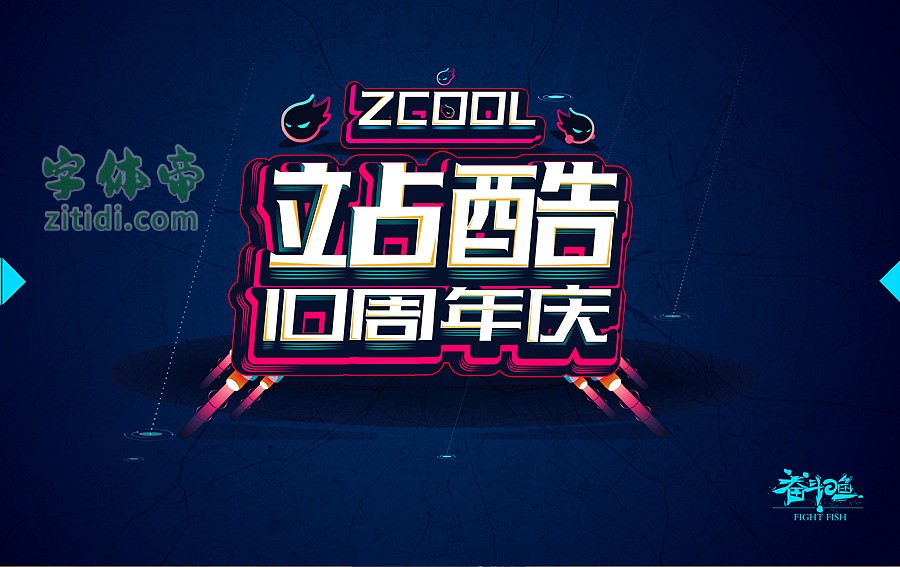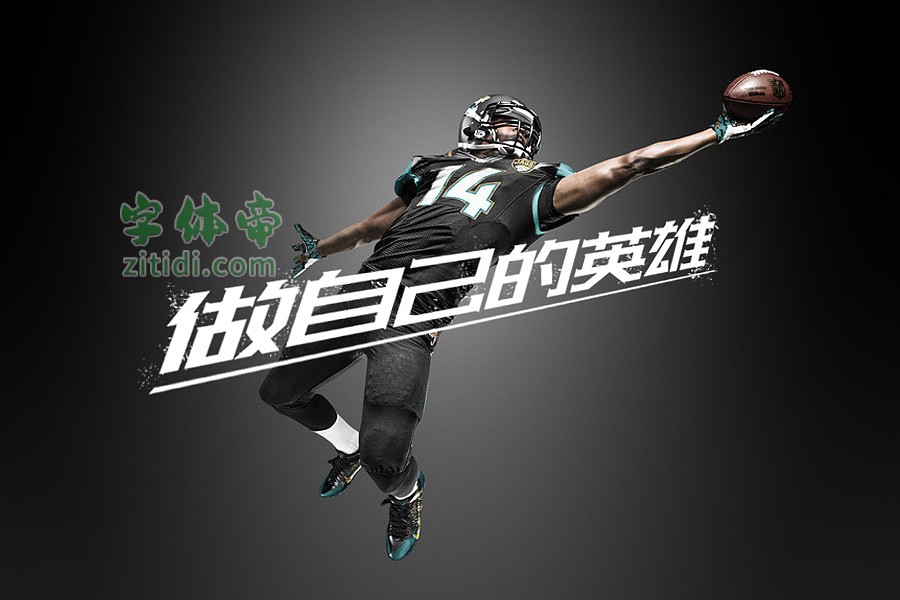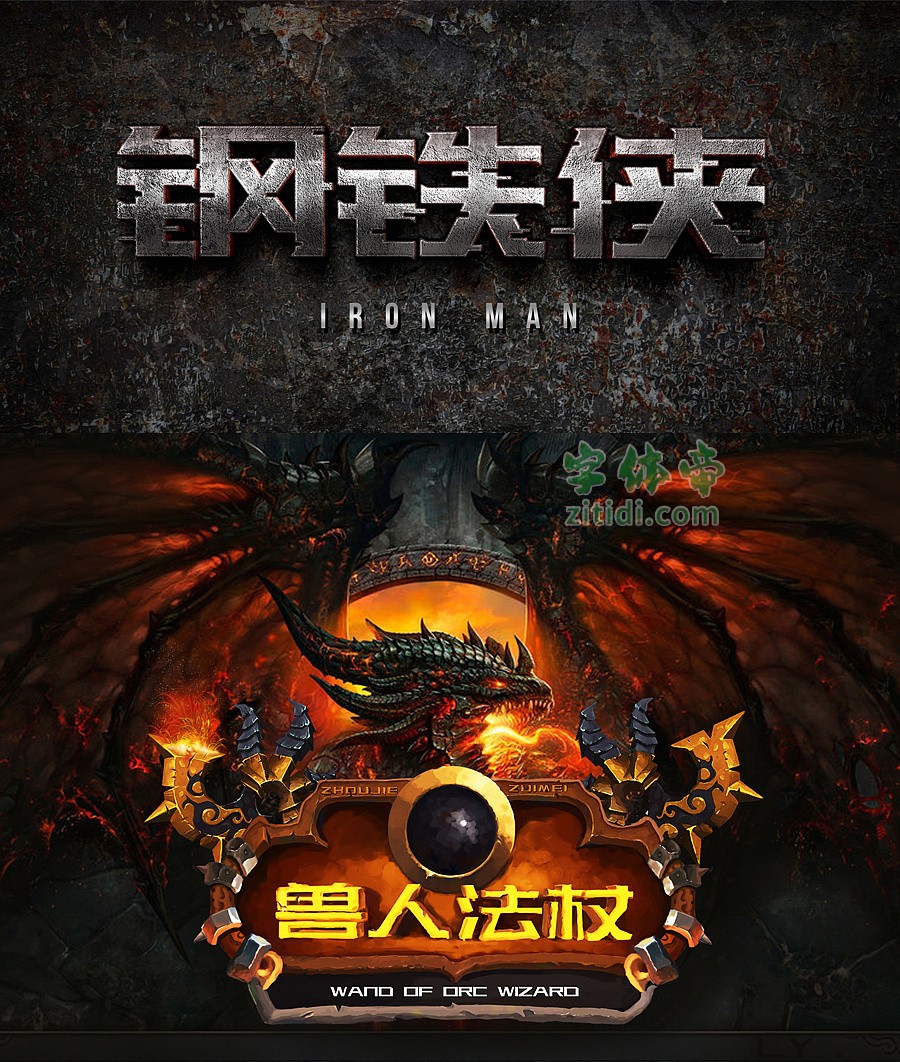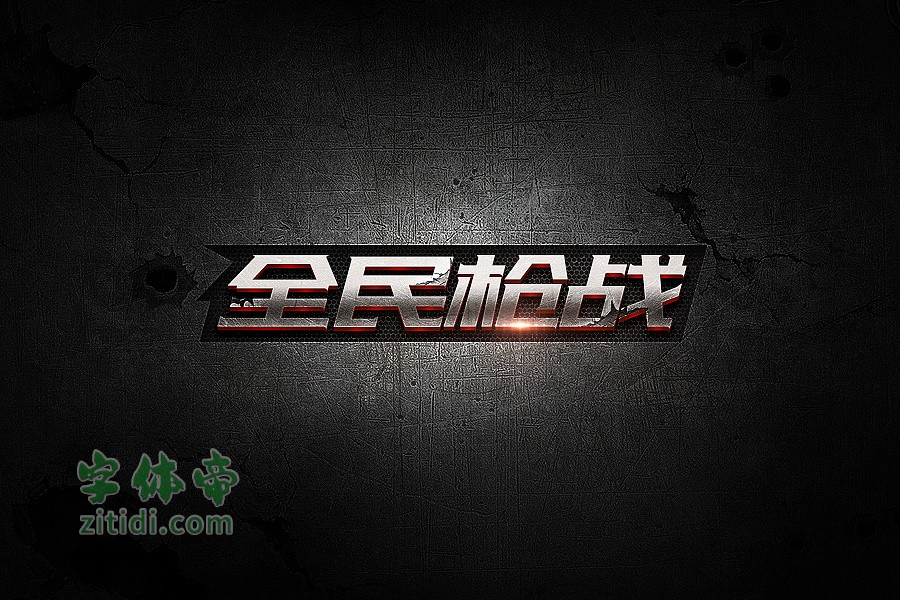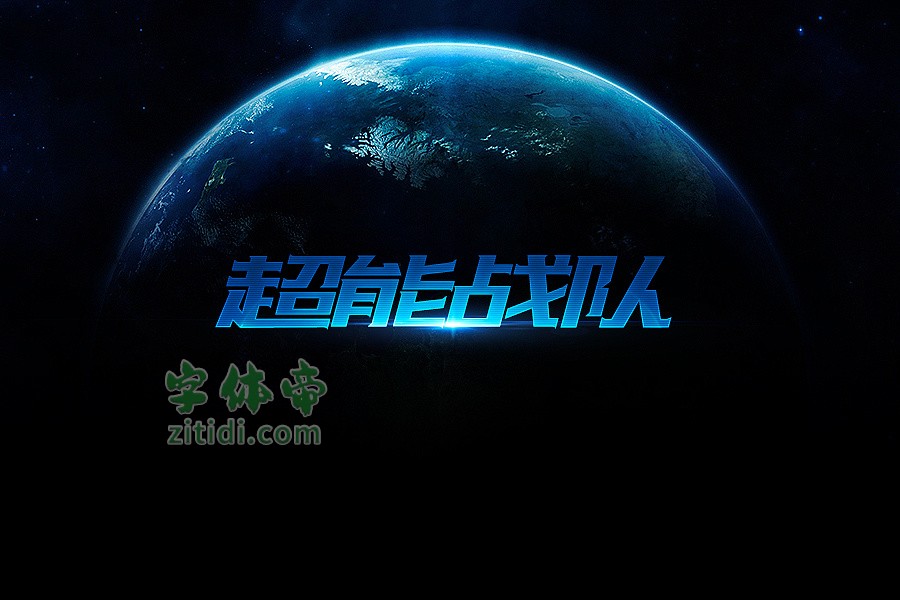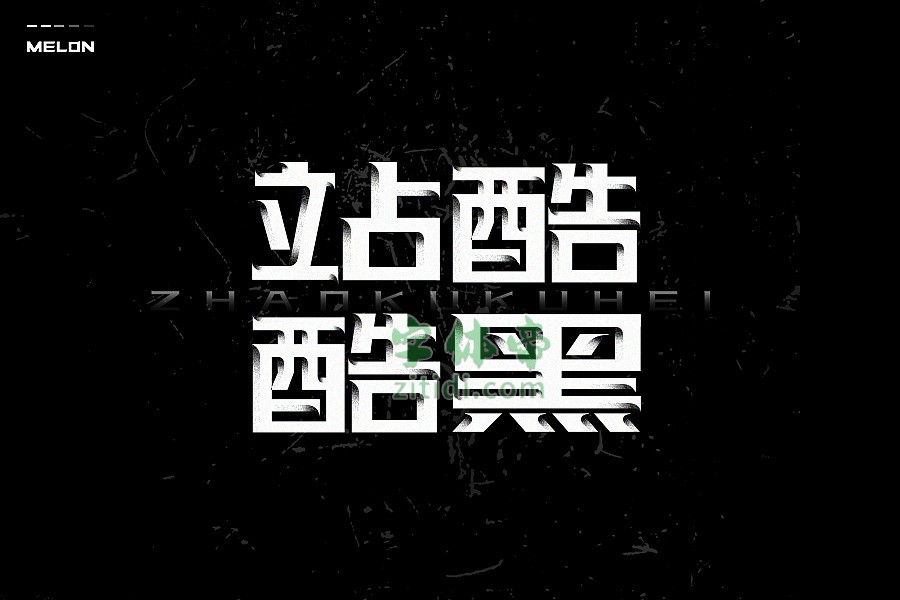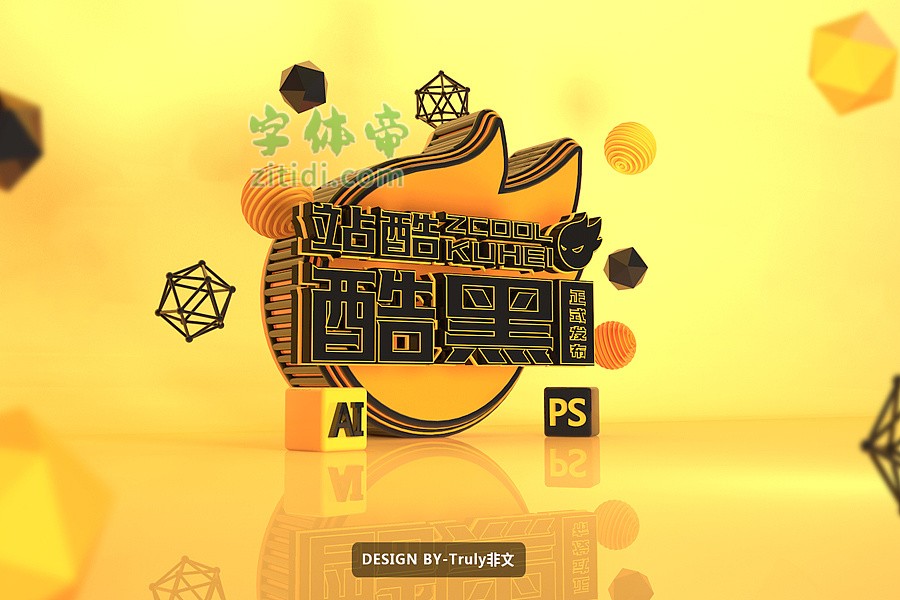
[站酷酷黑体验版]在站酷十周年之际横空出世。字形笔画粗犷有力,用宽扁型的字面构建出厚重的字体形态,笔画细节上的修饰既增强了字体的设计感,又让字体多了一些小小的精致感,中宫的饱满使得文字之间的排版组合非常醒目好看。2016年7月发布体验版。
站酷酷黑包含3500个常用字、52个英文字母、10个阿拉伯数字及诺干标点符号,先由工作室确定字形,设定框架结构,并且预先设计好偏旁部首,由十名同学一笔一划的设计完成(下载字库的页面有具体介绍),最后再由工作室王猛奇、王鹤群调整修改,并多次检查完成,直到最后编码生成字库,耗时大概三四个月。站酷酷黑字形笔画粗犷有力、用宽扁型的字面构建出厚重的字体形态,笔画细节上的修饰也是这款字体的亮点,也许酷黑依旧会存在一些问题,但是也不可否认这款字库的特有魅力!同时,市面上终于又多出一款完全免费的字体了,是的,完全免费!!
“站酷酷黑体”是一款书写很新颖的字体,字体大方,适合各种设计作品使用!欢迎下载!